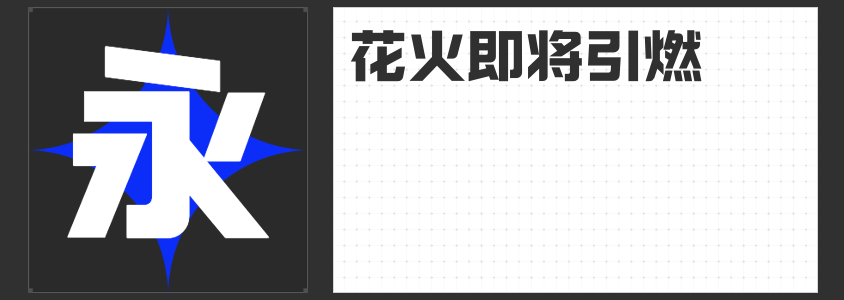
悬疑剧字体精选:为剧集增添视觉张力
在悬疑剧的世界里,每一个细节都至关重要,字体也不例外。合适的字体不仅能增强剧情的沉浸感,还能在视觉上为观众带来额外的享受。今天,我们就来推荐四款特别适合悬疑剧的四款字体。
首先,“励字勇敢黑简 常规”以其没有衬线装饰、笔划粗壮有力的特点脱颖而出。这款字体撇捺等笔画不尖,横直均匀,非常易于阅读,同时又能突出醒目。在悬疑剧中,它常被用于标题、导语和标志等关键位置,能够瞬间抓住观众的注意力,为剧情的展开埋下伏笔。
接下来,“造字侠朝凤宋简”以其宽扁工整、软硬兼备的特点,为悬疑剧增添了一抹独特的韵味。这款宋体的横笔画起笔左下角带有圆角,折笔处则带有方形特点,整体更具几何化美感。撇、捺、提笔画的曲线流畅,收笔处带有切笔凸起,点画为切笔半圆形,钩画外圆内方,整体兼备力量感与柔美感,韵美结合,极具表现力。在悬疑剧中,它能够很好地配合剧情的紧张氛围,营造出一种神秘而又不失优雅的感觉。
“造字侠热辣隶简”则是一款结合传统隶书特点与现代设计元素的创意隶书。这款字体整体结构稳定、中宫扁宽,具有较强视觉冲击力,给人庄重威严之感。在悬疑剧中,它常被用于强调某些关键信息或作为片头片尾的字幕,能够很好地凸显出剧情的严肃性和紧张感。
最后,“励字暴风简 超级黑”以其现代创意型黑体的特点,为悬疑剧带来了一股强烈的现代文艺气息。这款字体字型厚重略带一些开放性,笔画粗细做不均等形状,横竖笔画呈梯形分布。撇、捺、点等笔画加入了更多梯形元素,整体风格偏硬,横竖笔划的不规则感打破了传统的认知。在悬疑剧中,它能够很好地与剧情的紧张氛围相融合,为观众带来一种全新的视觉体验。
总之,这四款字体各有千秋,都能为悬疑剧增添不少色彩。不妨试试看,用它们来打造你的悬疑作品吧!